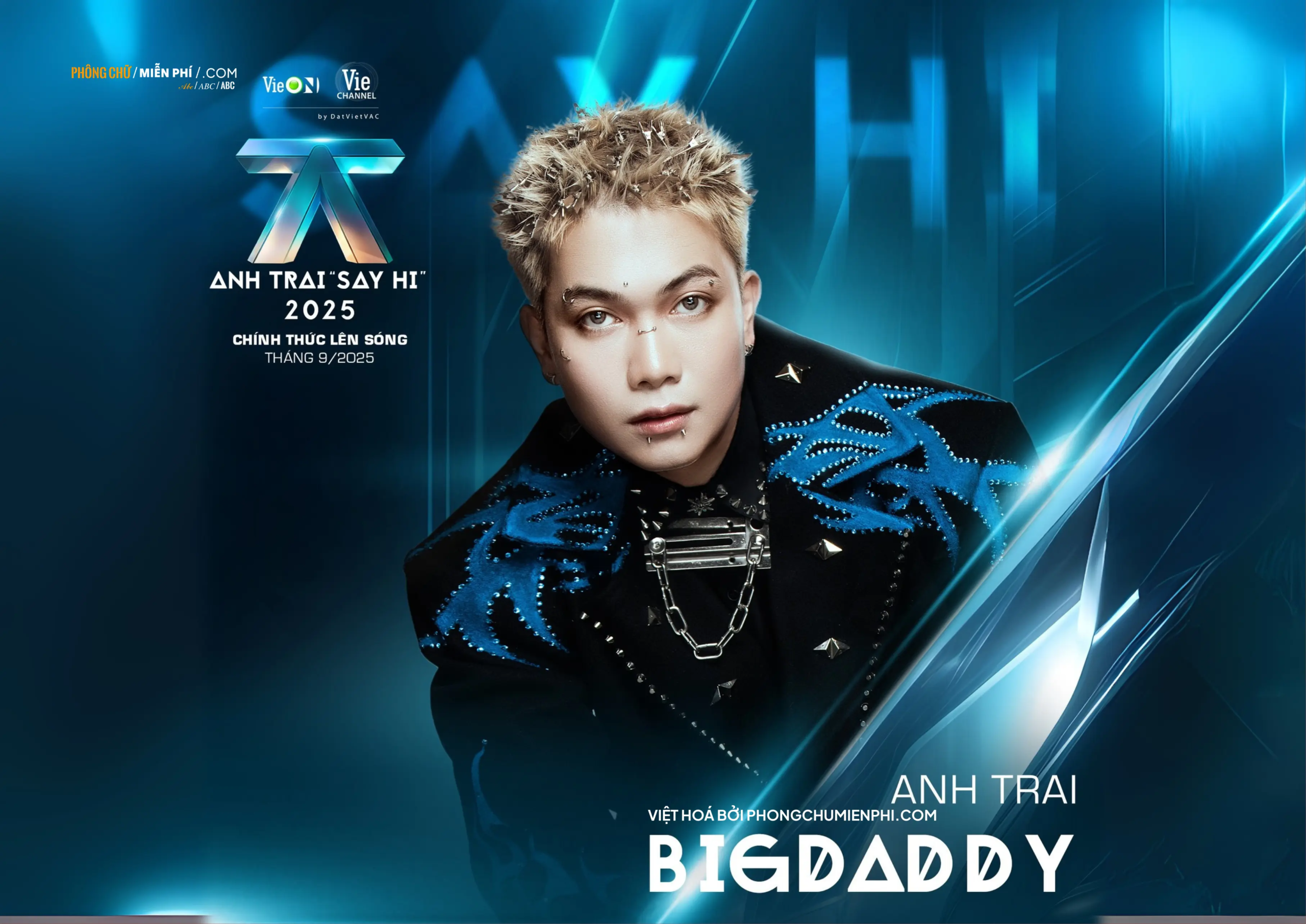
Tên font: Font Việt hoá Anh Trai Say Hi Jaapokkienchance ( Bộ 3 Font )
Font Anh Trai Say Hi Việt hóa PCMP Jaapokki Enchance Font
PCMP Jaapokkienchance – một phông chữ in đậm mang đậm dấu ấn hình học, được phongchumienphi.com Việt hoá tinh tế, đem đến trải nghiệm thị giác mạnh mẽ và hiện đại.
PCMP Jaapokki Enhance là một font Việt hoá thuộc nhóm sans-serif hiện đại, mang phong cách tối giản nhưng vẫn đầy sáng tạo. Được phát triển dựa trên phiên bản Jaapokki Regular, phiên bản Enhance nổi bật với những điểm nhấn hình học tinh tế ở các chữ in hoa, tạo nên hiệu ứng thị giác độc đáo và thu hút.
Với thiết kế gọn gàng, rõ ràng cùng các chi tiết cách điệu khéo léo, PCMP Jaapokki Enhance phù hợp cho nhiều dự án thiết kế như logo, tiêu đề, poster, banner, thương hiệu hay các ấn phẩm cần sự ấn tượng và khác biệt. Đây là lựa chọn lý tưởng cho những nhà thiết kế muốn kết hợp giữa sự tối giản hiện đại và dấu ấn sáng tạo tinh tế.
Font chữ anh trai say hi nổi bật với các khối hình góc cạnh sắc nét, đường nét gọn gàng và cấu trúc chắc chắn. Các chữ cái in hoa gây ấn tượng mạnh, đặc biệt là chữ “A” với dáng tam giác đầy cá tính và chữ “M” góc cạnh độc đáo. Chữ thường vẫn giữ nguyên phong cách hình học liền mạch, tạo cảm giác đồng nhất từ đầu đến cuối.
Không chỉ chữ cái, các con số cũng được thiết kế đậm, rõ ràng và dễ đọc, phù hợp cho cả tiêu đề lẫn nội dung. Các ký tự đặc biệt được trau chuốt theo cùng phong cách, góp phần tạo nên tổng thể hiện đại, tối giản nhưng đầy sức hút.
Với độ rộng nét đồng đều và bố cục hài hoà, PCMP Jaapokki Enchance là lựa chọn lý tưởng cho nhiều dự án thiết kế: từ logo, poster, bao bì sản phẩm cho tới ấn phẩm truyền thông cần sự nổi bật và cá tính.